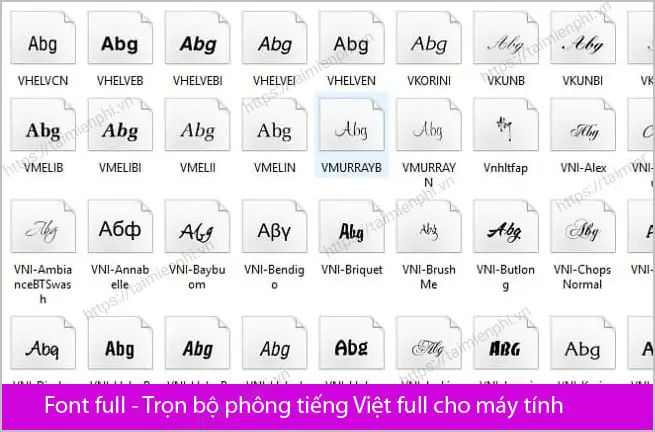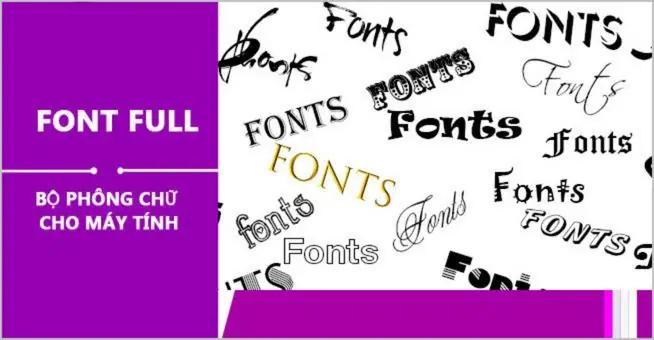
Font chữ tiếng Việt đầy đủ là bộ công cụ không thể thiếu cho bất kỳ ai làm việc với văn bản bằng tiếng Việt trên máy tính. Dù bạn là học sinh, sinh viên, nhân viên văn phòng hay designer chuyên nghiệp, việc sở hữu bộ font tiếng Việt chuẩn sẽ giúp tài liệu của bạn hiển thị đúng định dạng, tránh tình trạng lỗi font, chữ cái bị thay thế bằng ký tự lạ. Bài viết này sẽ cung cấp link tải bộ font tiếng Việt đầy đủ mới nhất 2025, hướng dẫn cài đặt chi tiết và chia sẻ bí quyết chọn font phù hợp với từng mục đích sử dụng.
Bộ Font Tiếng Việt Đầy Đủ Mới Nhất 2025
Bộ font tiếng Việt đầy đủ mới nhất 2025 bao gồm hơn 500 font chữ chất lượng cao, được cập nhật liên tục để tương thích với các hệ điều hành Windows, macOS và Linux. Bộ sưu tập này chia thành 5 nhóm chính: font chữ viết tay tự nhiên, font chữ hiện đại trẻ trung, font chữ cổ điển trang nhã, font chữ kỹ thuật công nghiệp và font chữ nghệ thuật sáng tạo. Mỗi font đều được kiểm tra kỹ lưỡng về khả năng hiển thị tiếng Việt có dấu, đảm bảo không bị lỗi khi gõ các ký tự đặc biệt như ă, â, đ, ê, ô, ơ, ư.
Phân Loại Font Chữ Tiếng Việt Theo Mục Đích Sử Dụng
Font chữ cho văn bản hành chính
Font Times New Roman, Arial và Courier New vẫn là lựa chọn hàng đầu cho các văn bản hành chính, công văn, quyết định. Những font này mang tính trang trọng, dễ đọc và được sử dụng rộng rãi trong các cơ quan nhà nước. Ngoài ra, các font như Roboto, Calibri cũng đang được ưa chuộng nhờ thiết kế hiện đại nhưng vẫn đảm bảo tính chuyên nghiệp. Đối với font tiếng Việt, bạn cần chọn các phiên bản đã được Việt hóa đầy đủ để tránh lỗi font khi in ấn.